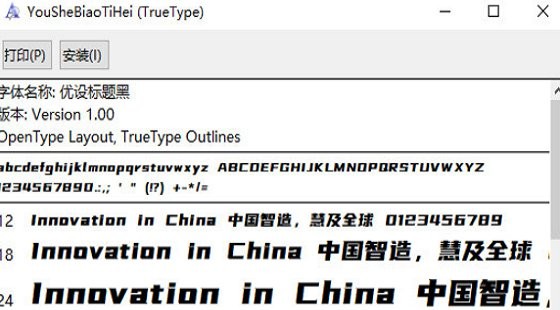
※用在各類品牌廣告和產(chǎn)品包裝設(shè)計(jì)的標(biāo)題上,最合適不過
※它以黑體字型為基礎(chǔ),整體字形沉穩(wěn),同時(shí)采用較大字面和粗壯的筆畫來強(qiáng)化力量感。每個(gè)字體水平傾斜8°的設(shè)計(jì),賦予了字體極強(qiáng)的速度感,為了讓字體傾斜后也能保持穩(wěn)固,設(shè)計(jì)師將整體字身設(shè)定寬扁。而起筆和彎鉤上獨(dú)具匠心的尖角設(shè)計(jì),不僅突顯了設(shè)計(jì)的幾何感,而且方便后期修改。
2、改字體帶有一點(diǎn)傾斜效果,正式感的同時(shí)又不是藝術(shù)感